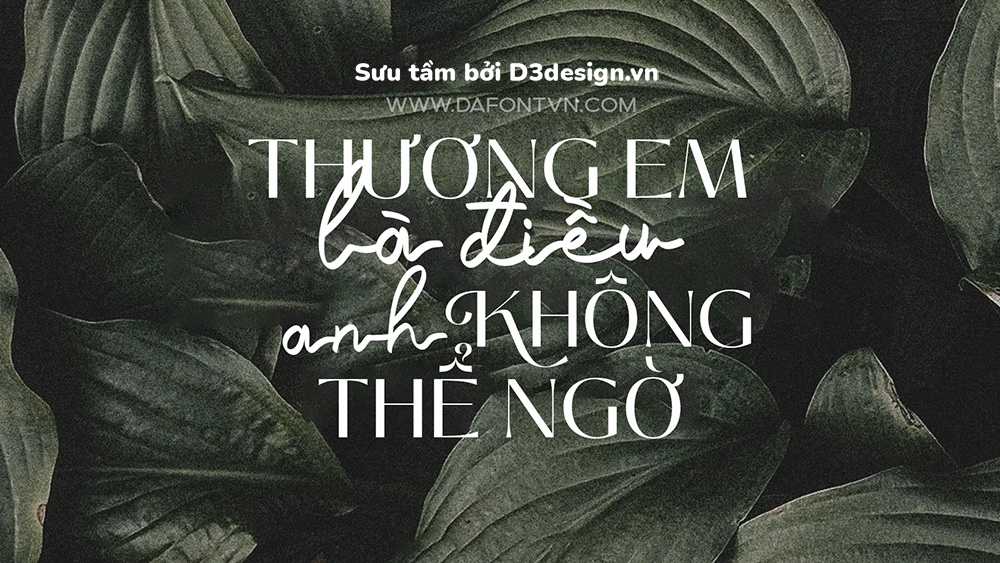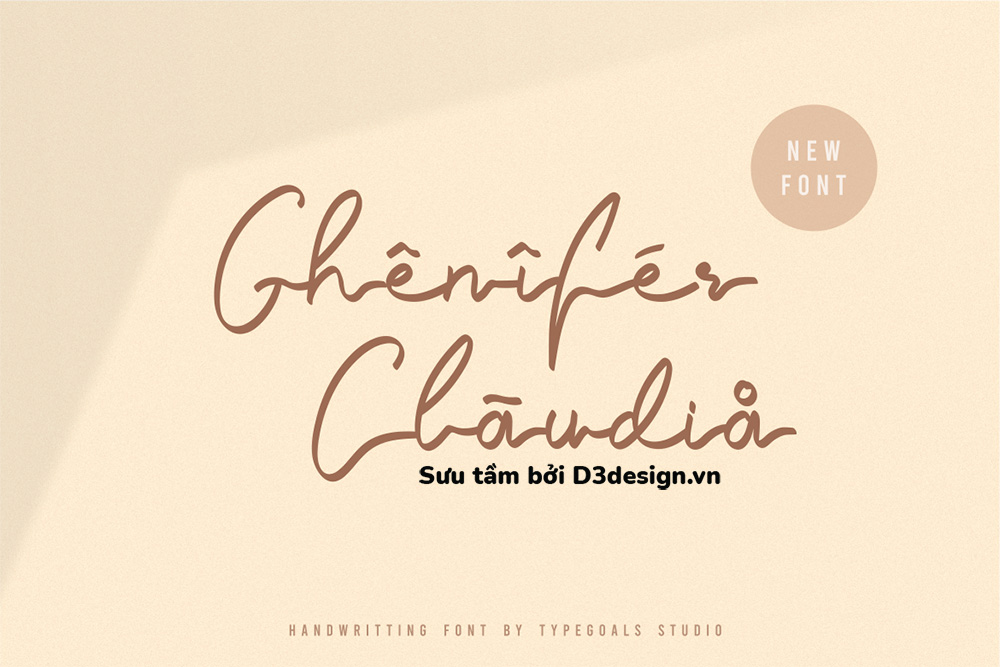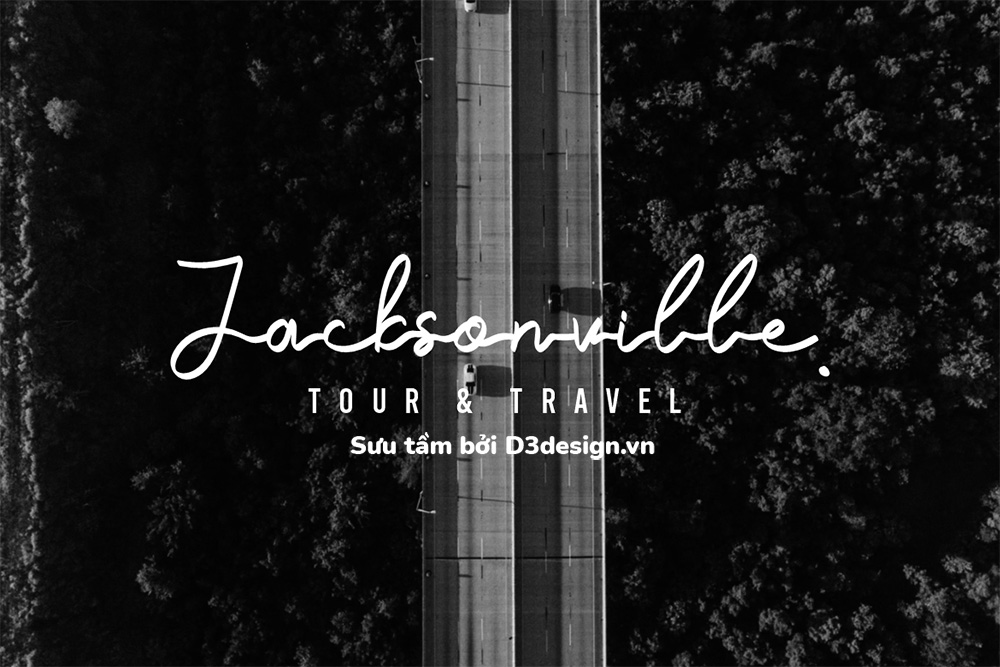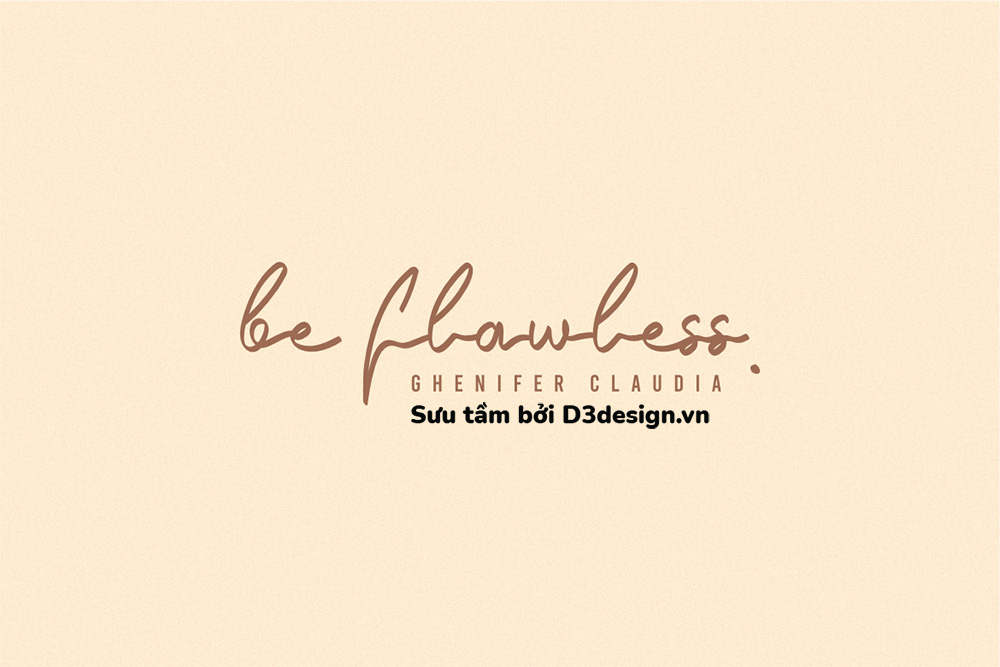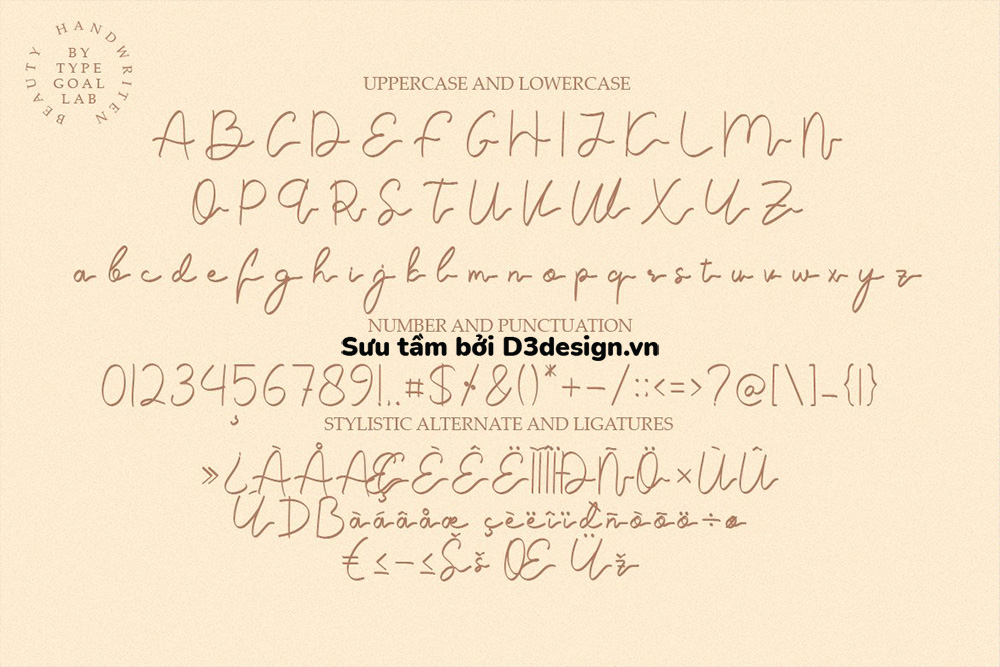
Font Việt Hóa - Ghenifer Claudia Mang Phong Cách Thanh Lịch, Hiện Đại
Ghenifer Claudia Font Việt Hóa - là một font chữ viết tay với một thiết kế độc đáo mang đến điểm nhấn của riêng nó và những nét mực thanh lịch. Phông chữ viết tay Ghenifer Claudia hoàn hảo cho các dự án xây dựng thương hiệu, logo, thiệp đám cưới, quảng cáo, bao bì sản phẩm, thư mời...